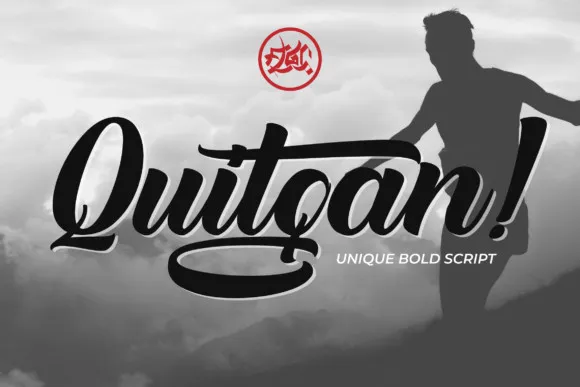
Quitgan Bold Script Font – Fonte Grátis
Quitgan Bold Script Font
Esta fonte script Quitgan Bold é uma peça incrível para quem busca uma tipografia casual mas com forte personalidade. Ela foi criada a mão com muitos recursos OpenType, tornando-a perfeita para incorporar em diversos ambientes de design. Suas linhas modernas e suas abstrações inovadoras fizeram dela um design único, ideal para nomes de marca, assinaturas pessoais, fotografia e qualquer necessidade de design. Quem adora uma tipografia que saia da caixa, vai amar Quitgan Bold Script. Seu estilo casual mas bold lhe dará liberdade para expressar a sua personalidade no seu próximo projeto. E o melhor? Acessível tanto em tamanhos grandes quanto pequenos, esta fonte é um excelente complemento para qualquer design, tornando-a indispensável em uma variedade de projetos. Introduzindo Quitgan Bold Script, você adquire mais uma ferramenta poderosa para seu arsenal de criação visual.